小楷,顾名思义,是楷书之小者,创始于三国魏时的锺繇,他原是位隶书最杰出的权威大家,所作楷书的笔意,亦脱胎于汉隶,笔势恍如飞鸿戏海,极生动之致。惟结体宽扁,横画长而直画短,仍存隶分的遗意,然已备尽楷法,实为正书之祖。到了东晋王羲之,将小楷书法更加以悉心钻研,使之达到了尽善尽美的境界,亦奠立了中国小楷书法优美的欣赏标准。
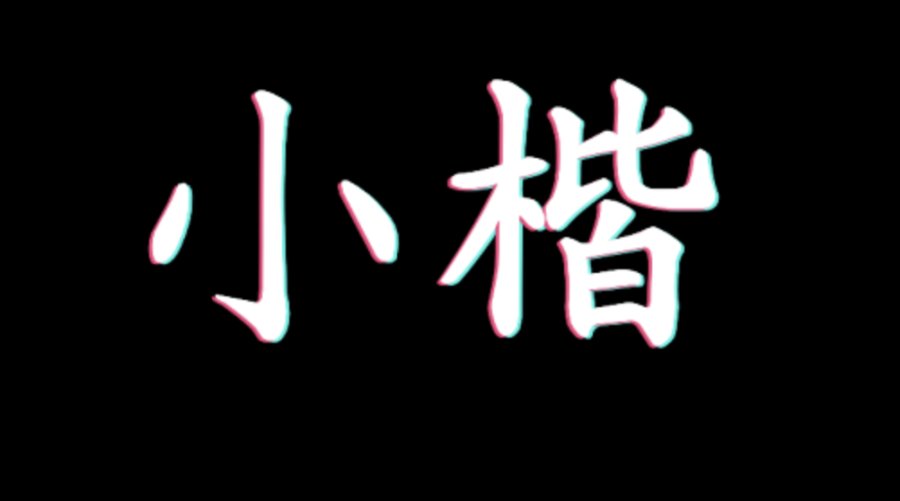
一般说来,写小字与写大字是大不相同的,其原则上是:写大字要紧密无间,而写小字必要使其宽绰有余。也就是说:写大字要能做到小字似的精密;而写小字要能做到有大字似的局促,故古人所谓“作大字要如小字,而作小字要如大字。”又苏东坡论书有“大字难于结密而无间,小字难于宽绰有余”的精语。以上这些话怎么讲呢?因为我们通常写大字时,以为地位(面积)宽阔,可以任意挥洒,结果字体变成了松散空阔。写小字则正好相反,因为地空间太小,担心写不下就越难免要尽力局缩,往往局缩过当,反而变成蜷促。这都是自然而然的心理现象,极易触犯的毛病。所以苏公“大小难能”这句话,正是针对这种神情而发,更是经验老到之谈。
写小字的重心与笔画的配合,则与大字无大差异。至于运笔,则略有不同。小字运笔要圆润、娟秀、挺拔、整齐;大字要雄壮、厚重。大字下笔时用逆锋(藏锋),收笔时用回锋;小字下笔时则不必用逆锋,宜用尖锋,收笔时宜用顿笔或提笔。譬如写一横,起笔处或尖而收笔处则圆;写一竖,起笔或略顿,收笔则尖;撇笔则起笔或肥而收笔瘦:捺笔则起笔或瘦而收笔肥,同时也要向左向右略作弧形,笔画生动而有情致;点欲尖而圆,挑欲尖而锐,弯欲内方而外圆,钩半曲半直。运笔灵活多变,莫可限定。尤其是整篇字,要笔笔不同,而又协调一致,一行字写出来,错落有致,却又一直在一条线上,如是则行气自然贯串,望之如串串珍珠项链,神采飞扬。
小字为古代日用必需的书法,以前科举应试时,阅卷的人大半是先看字,然后再看文章。字如不好,文章再好也要受影响。朝考状元、翰林,尤注重书法。是故凡状元、翰林的小字,都是精妙的。一般读书,也都善写小字。如今硬笔盛行,用毛笔写小字的人不多,但用硬笔临写小楷字帖有事半功倍的明显进效,因此想写好硬笔字,不妨找本好的小楷字帖,加工练习。定能打下坚实基础,裨益终身,受用不尽。
小楷字帖甚多,传世的墨拓中,要以晋唐小楷的声名最为显赫。其中通常包括了魏时锺繇的《宣示帖》《荐季直表》,东晋王羲之的《乐毅论》《曹娥碑》《黄庭经》王献之的《洛神赋十三行》、唐钟绍京的《灵飞经》等。还有元赵孟頫、明王宠、祝允明等小楷作品的墨迹影印本也是非常好的范本。
锺繇书法,具古朴风格,惟传世作品《宣示表》《荐季直表》,无一确实者,多为后人传模或临作。欣赏好的摹拓本,可以想像其古雅书风。